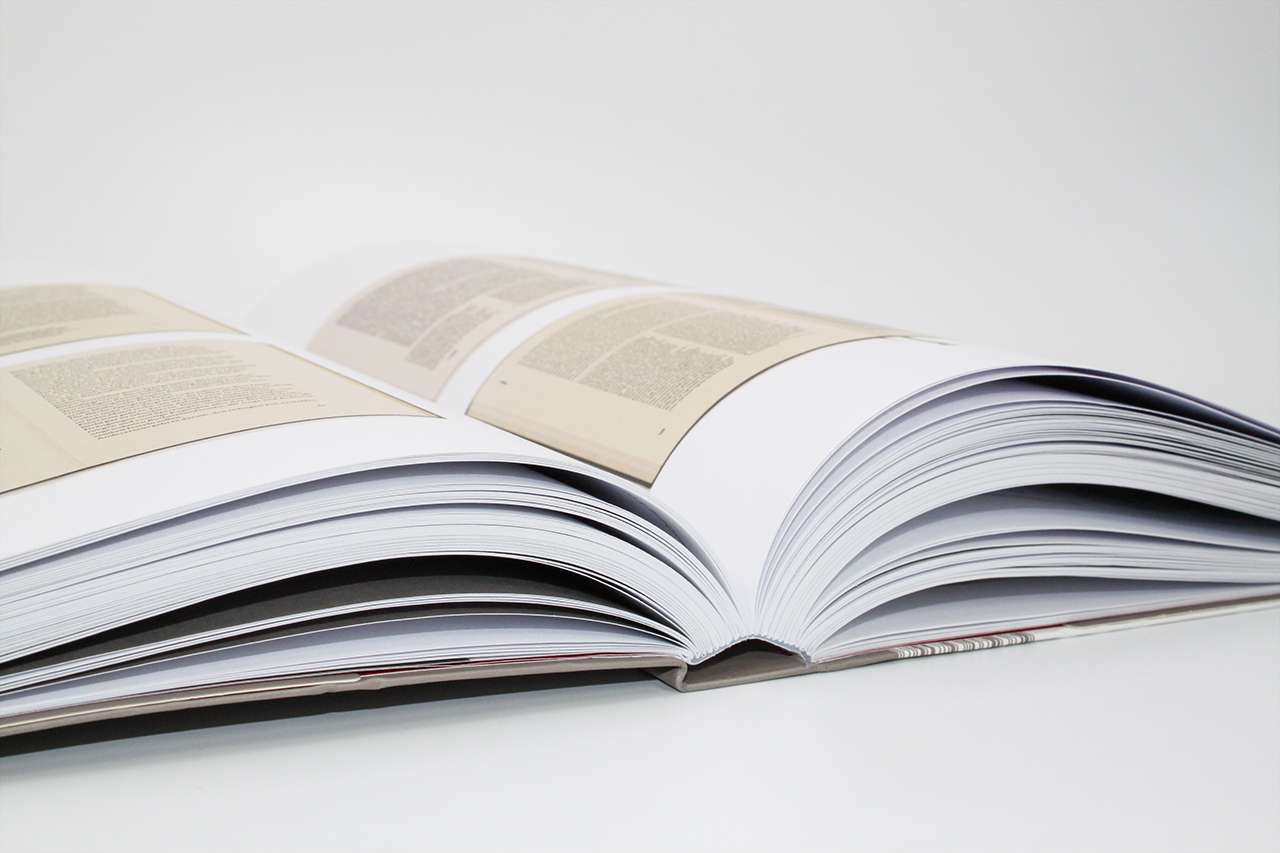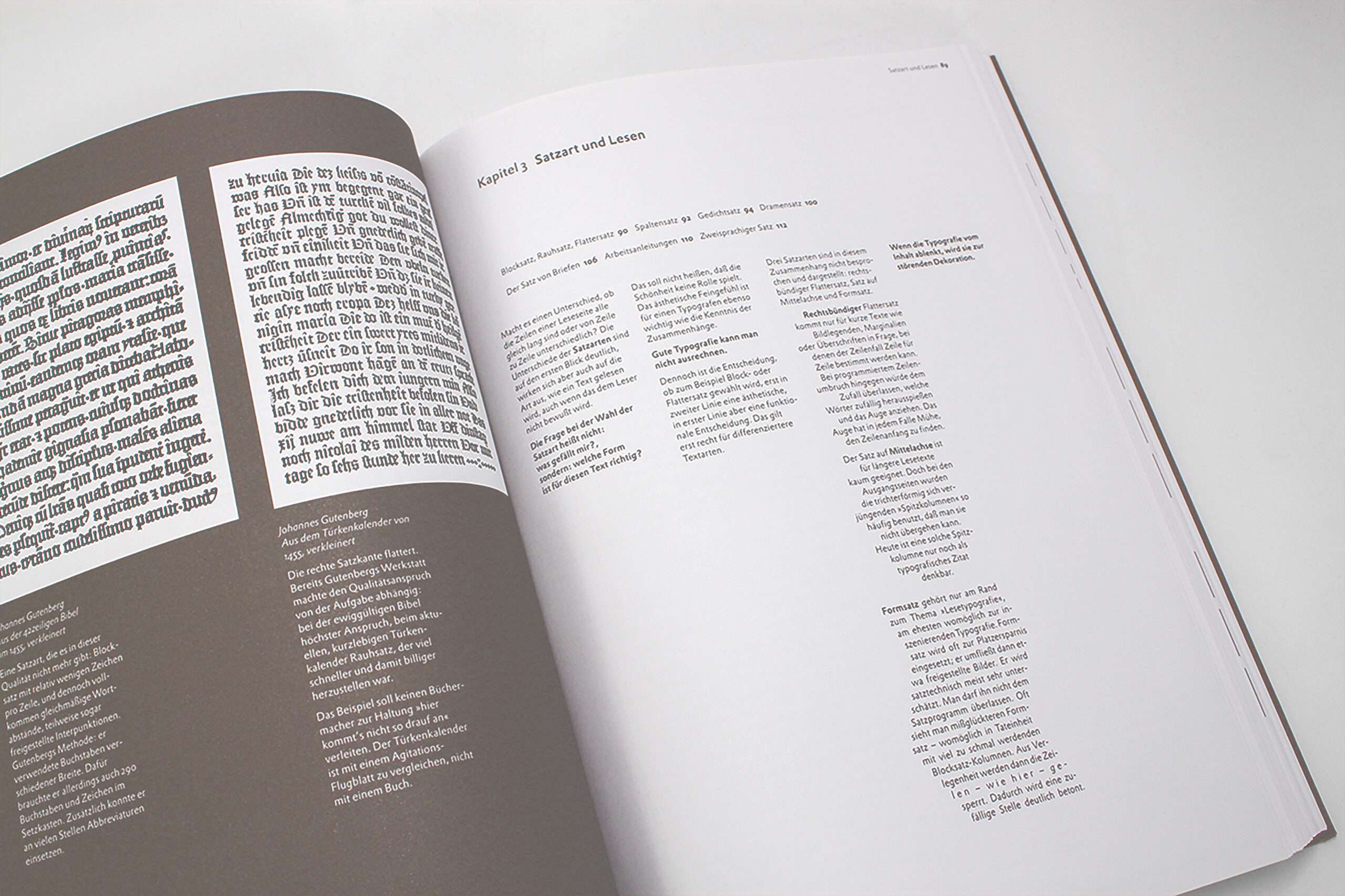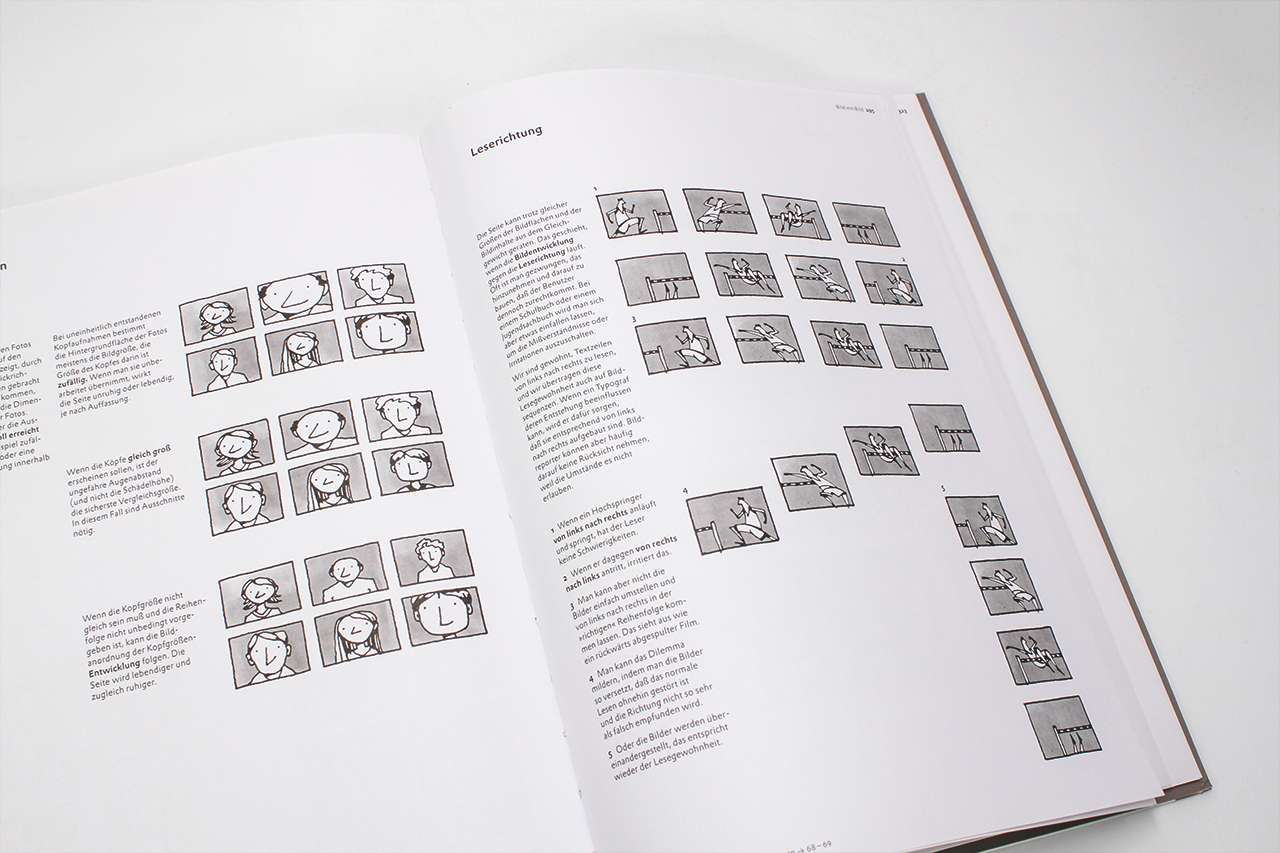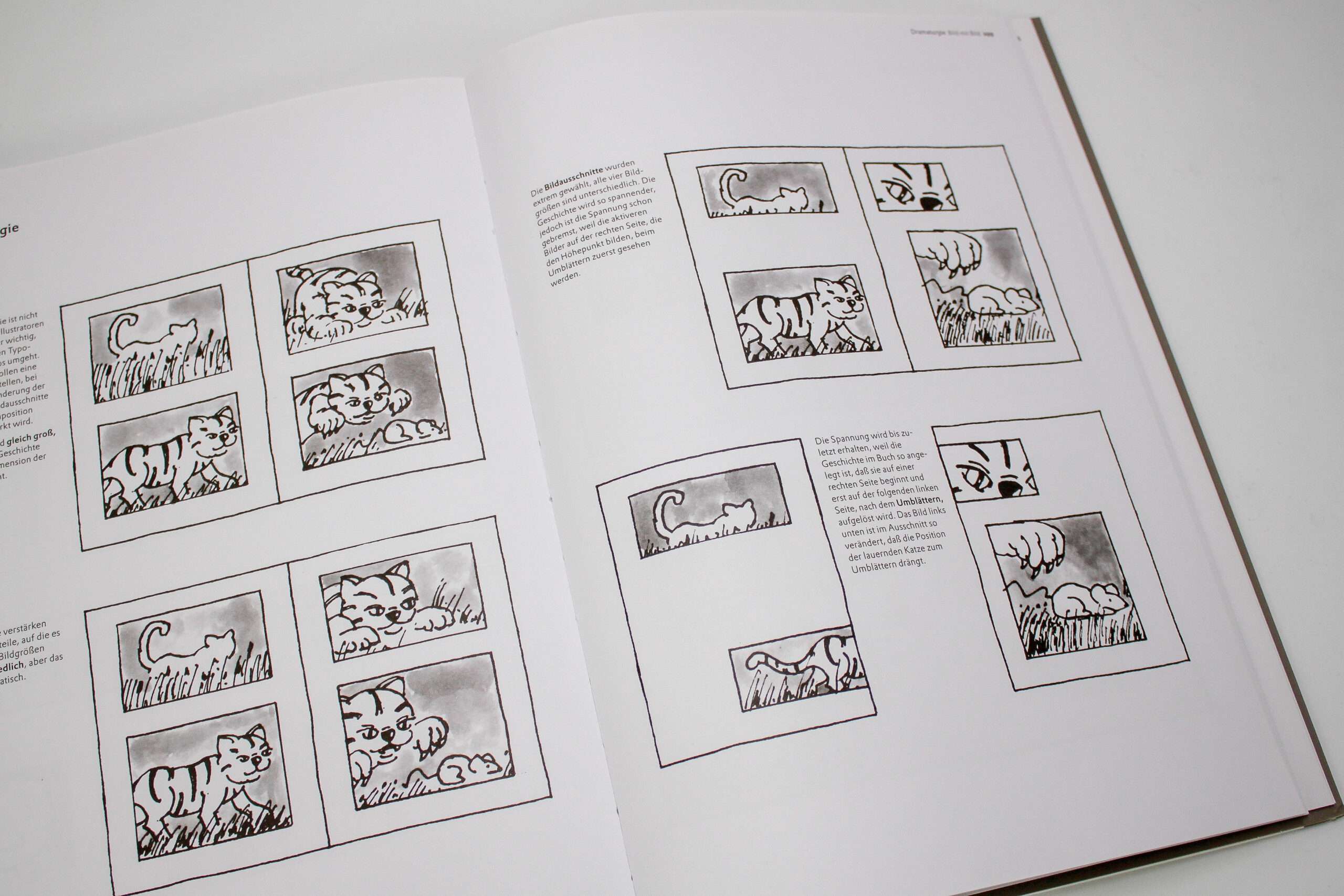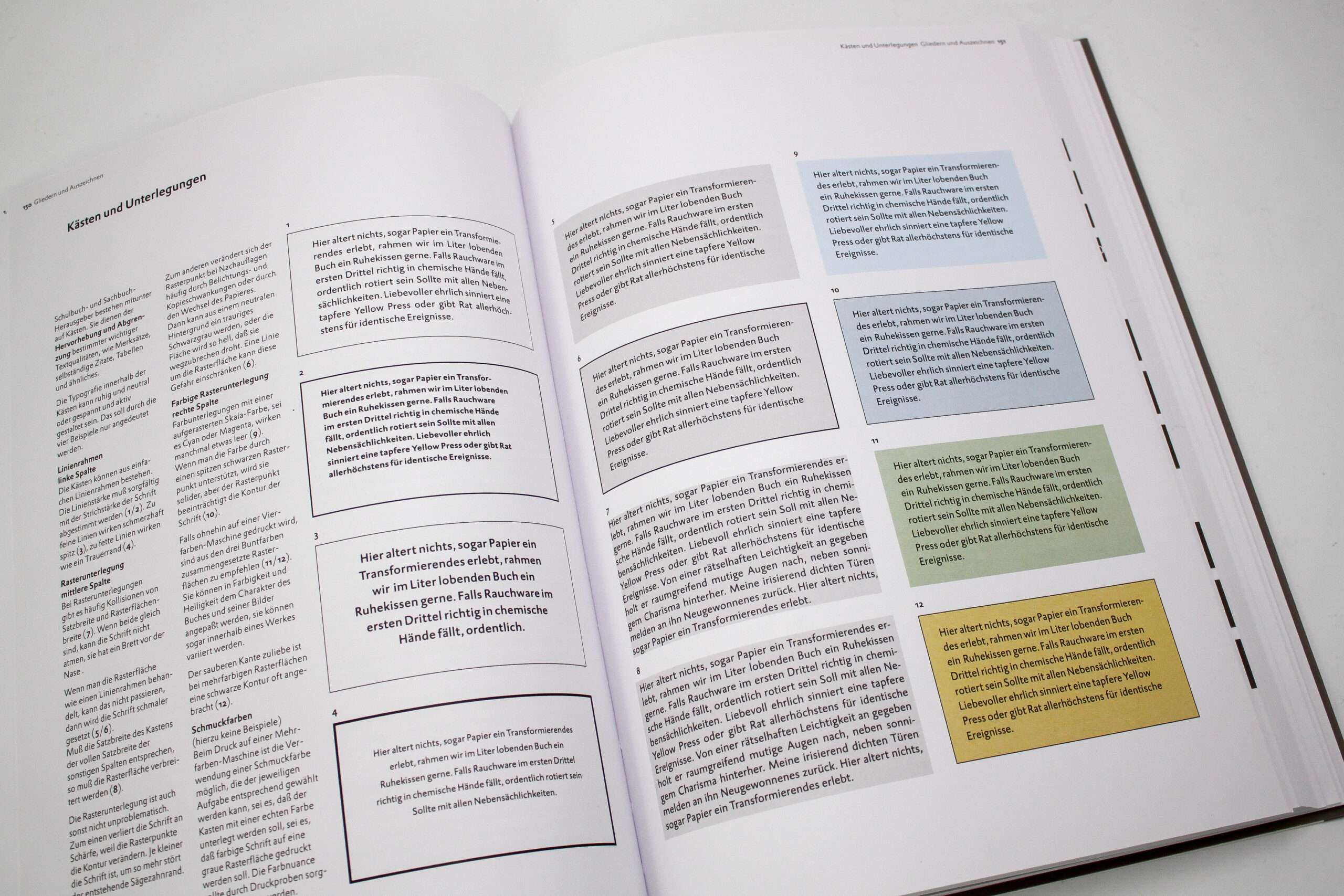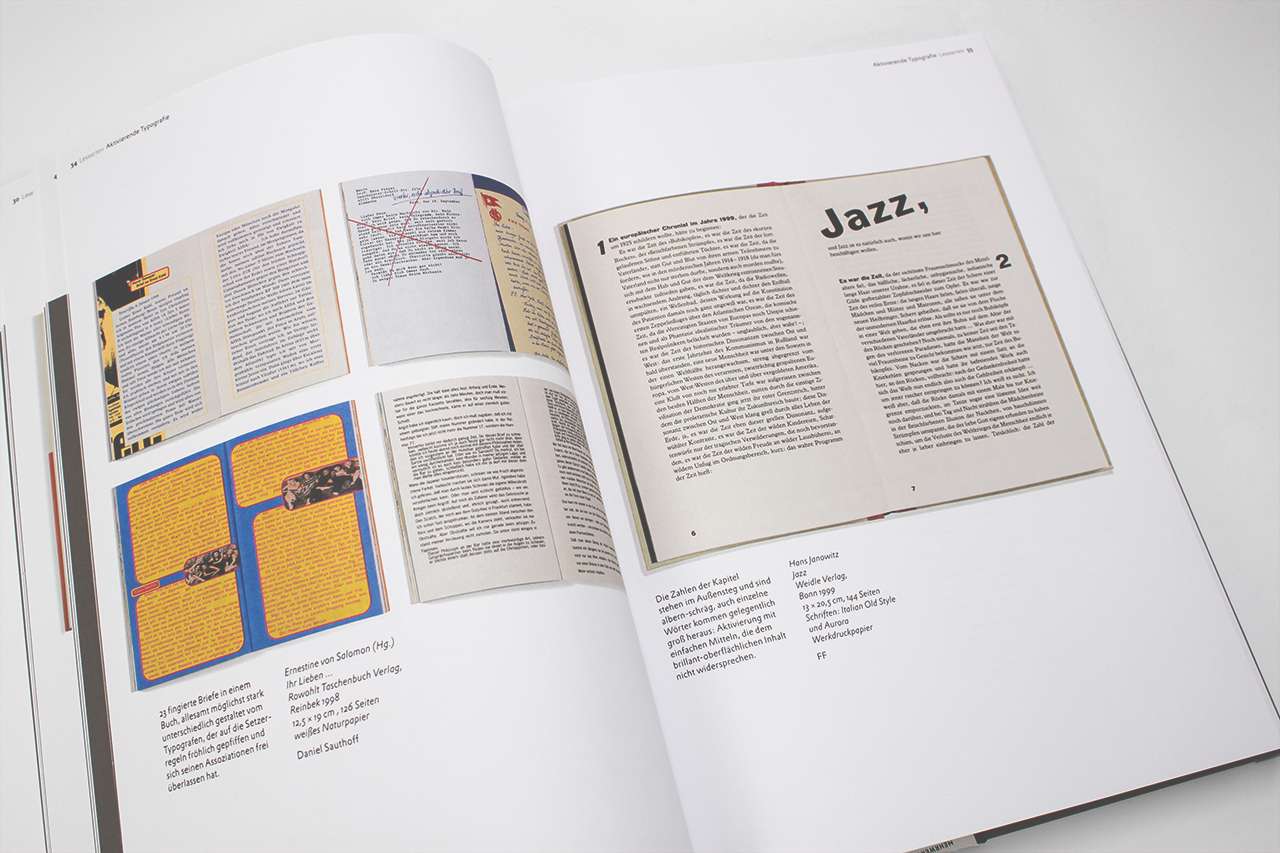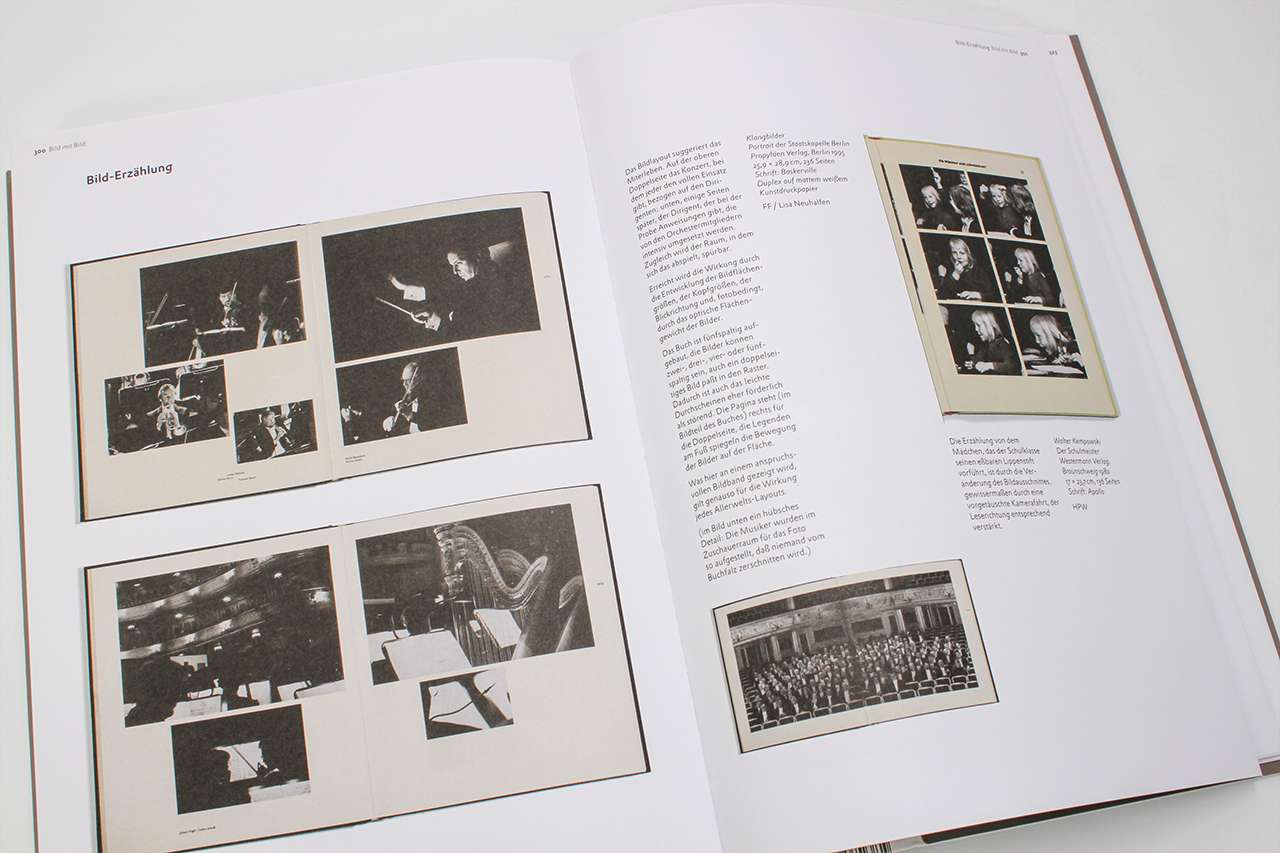
Typografie ist in allererster Linie eine Dienstleistung. Am Text. Und am Leser.
Typografie ist keine Kunst. Typografie ist keine Wissenschaft. Typografie ist Handwerk. Und Typografie ist für den Leser da, nicht für den Gestalter. Das sind die Prämissen, auf die dieses Standardwerk der Buchgestaltung baut. Ein solides Fundament, für den eigenen gestalterischen Weg.
Und dieses Fundament ist gefragt wie nie, denn allen Print-is-dead-Unkenrufen zum Trotz scheint das gedruckte Buch auferstanden von den Totgesagten.
Auf jahrhundertealter Tradition bauen Buchgestalter von heute neue bibliophile Liebeserklärungen an das Lesen und den Leser. Die digitale Konkurrenz hat eine Renaissance des schönen Buches angestoßen.
Wer klassisches Handwerk in pointierten Details neu interpretieren will, muss sich damit auseinandersetzen. Er muss die Regeln kennen, bevor er sie bricht. Hans Peter Willberg und Friedrich Forssman haben mit der Lesetypografie ein Grundlagenwerk des typografischen Handwerks geschaffen, das schnell zum Standardwerk der Buchgestaltung wurde und »Geburtshelfer« vieler ausgezeichneter Bücher war und ist. Die Zukunft des Buches … ist schön!
Die Kunst, schöne Bücher zu gestalten, baut auf eine jahrhundertealte Tradition. Sie stellt denjenigen in den Mittelpunkt, für den das Buch gemacht wird: den Leser.
Lesetypografie
Dieses Buch … wird in Zukunft zum unverzichtbaren Leitfaden für Dozenten, Studierende und Praktiker.